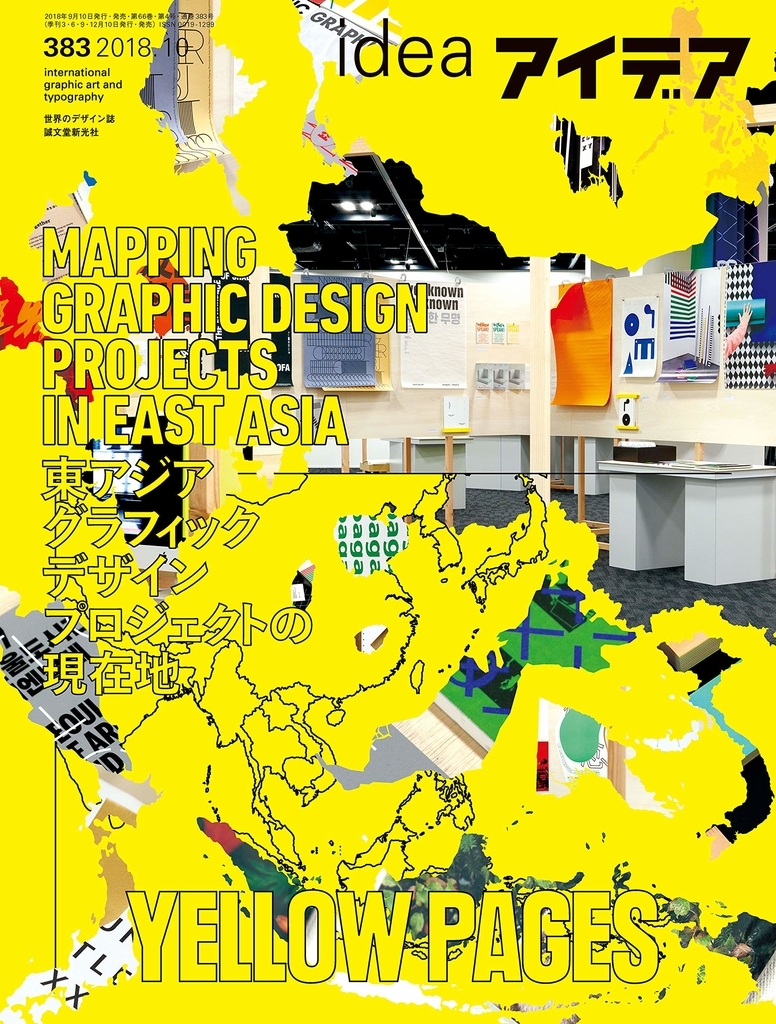
東アジアのグラフィックデザインプロジェクトの現在地を特集した「アイデア 2018年10月号」が誠文堂新光社から2018年9月10日に発売された。
また、デザイン史家・グラフィックデザイナーの佐賀一郎氏による2018年4月27日(金)~7月16日(月・祝)まで横浜開港資料館で開催された「金属活字と明治の横浜――小宮山博史コレクションを中心に」展の展示会レポート記事が掲載。記事では「金属活字と明治の横浜――小宮山博史コレクションを中心に」と小宮山博史氏のコレクションが持つ意義について考察された。
そのほか、長田年伸氏の記事として、2018年6月8日に発売された向井裕一氏著書「日本語組版入門: その構造とアルゴリズム」を読み解く為の『日本語組版入門』に入門するための5つの補助線」なども掲載されている。
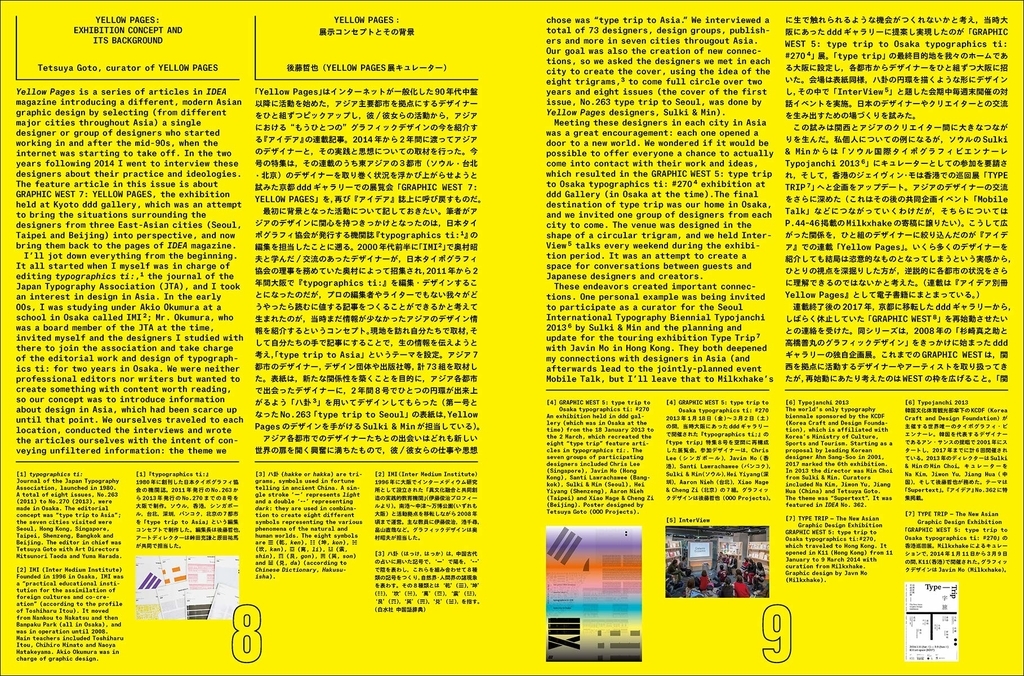
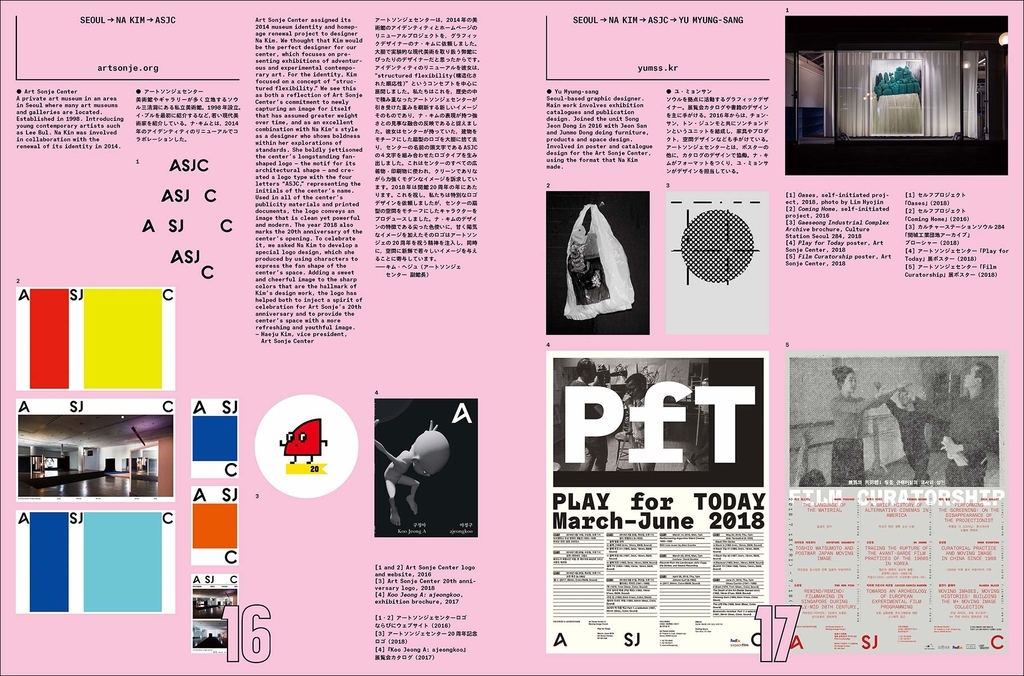
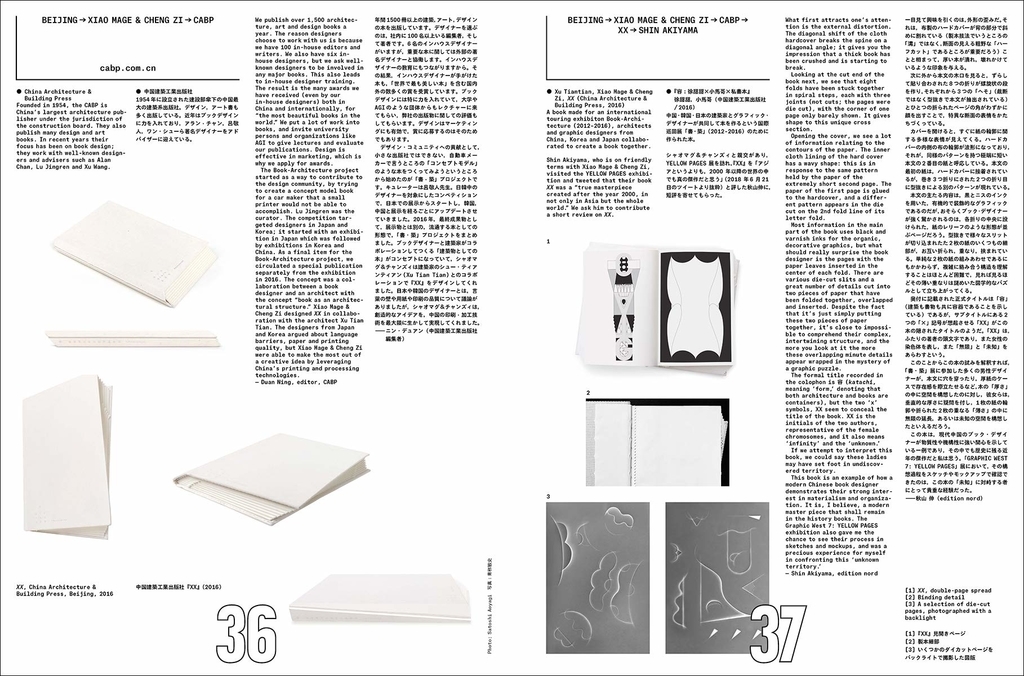
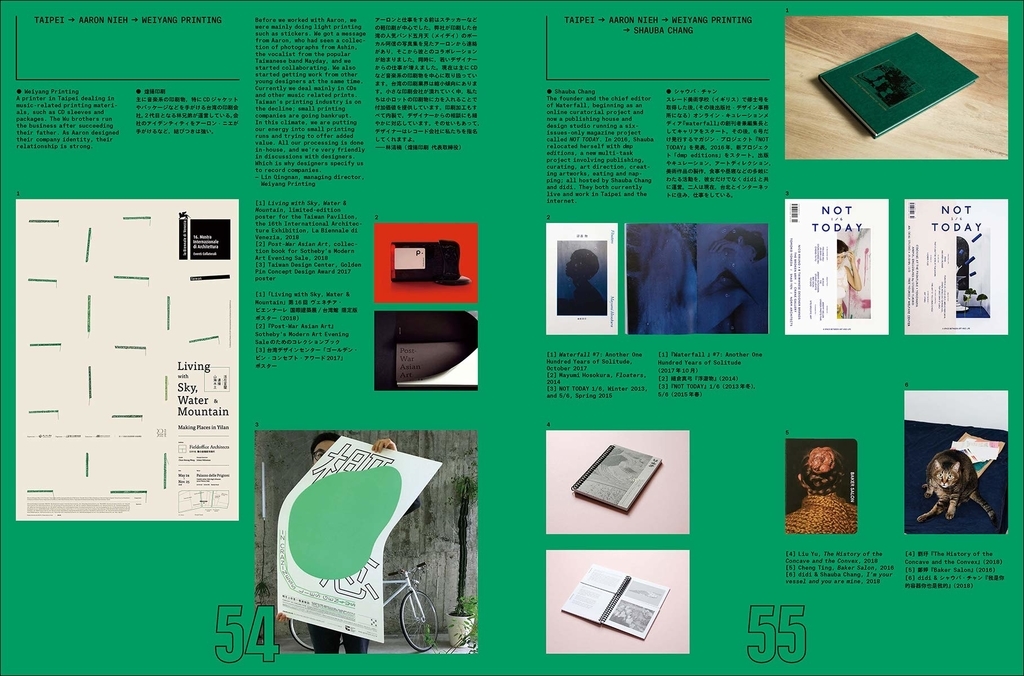
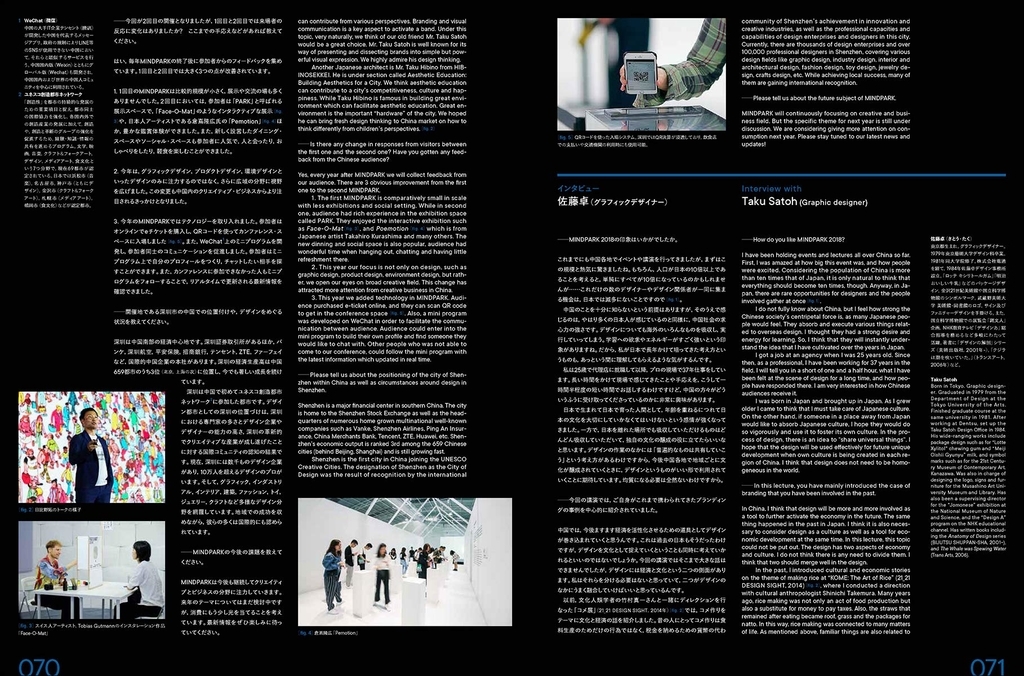
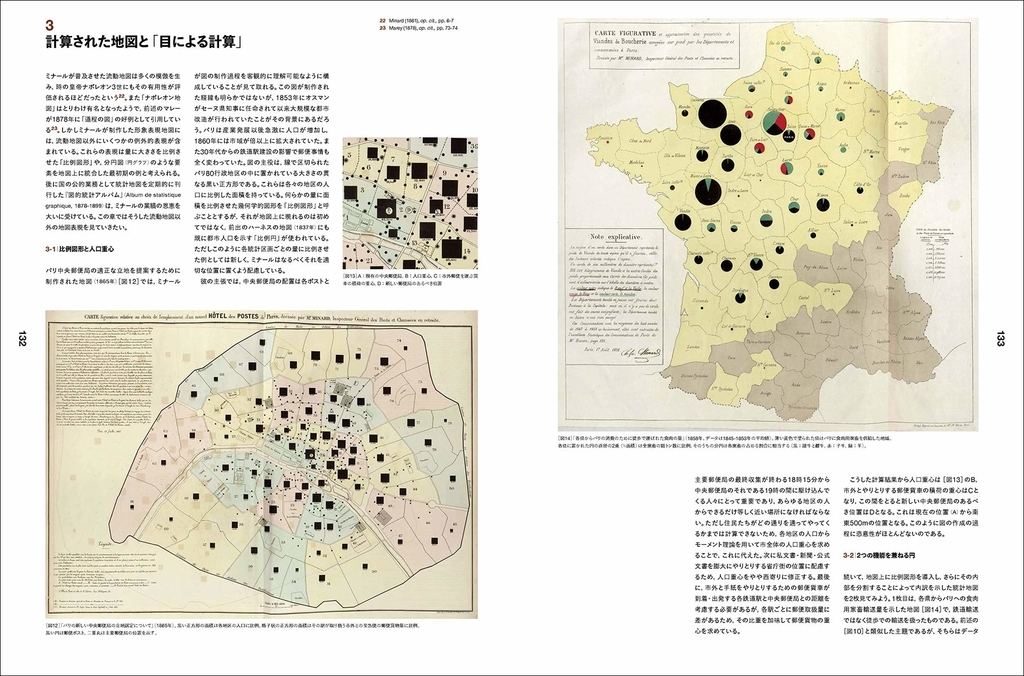
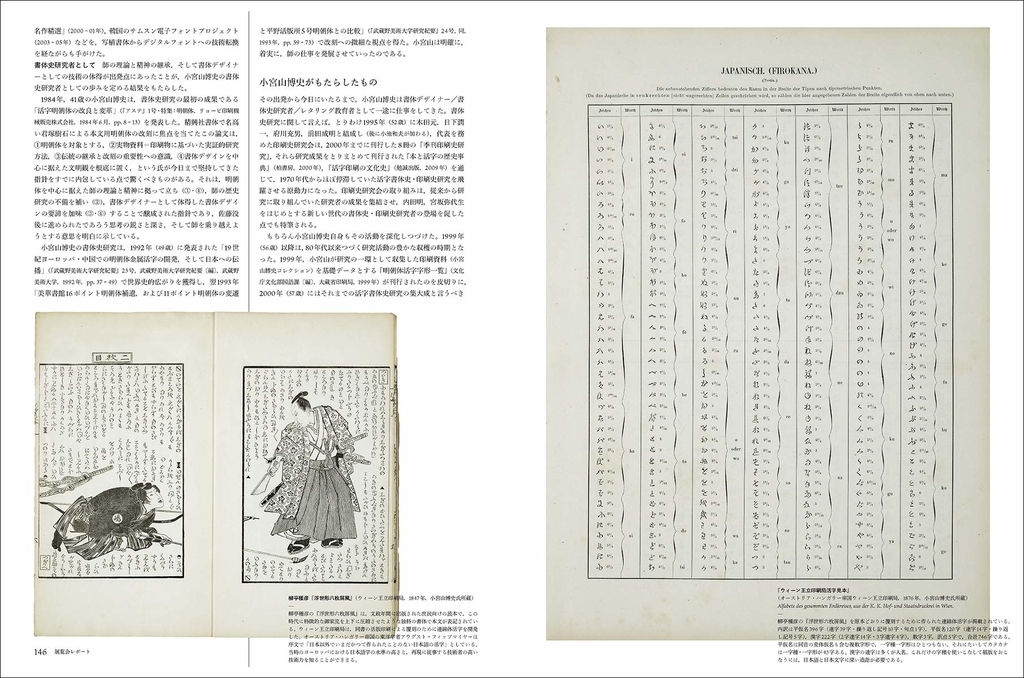
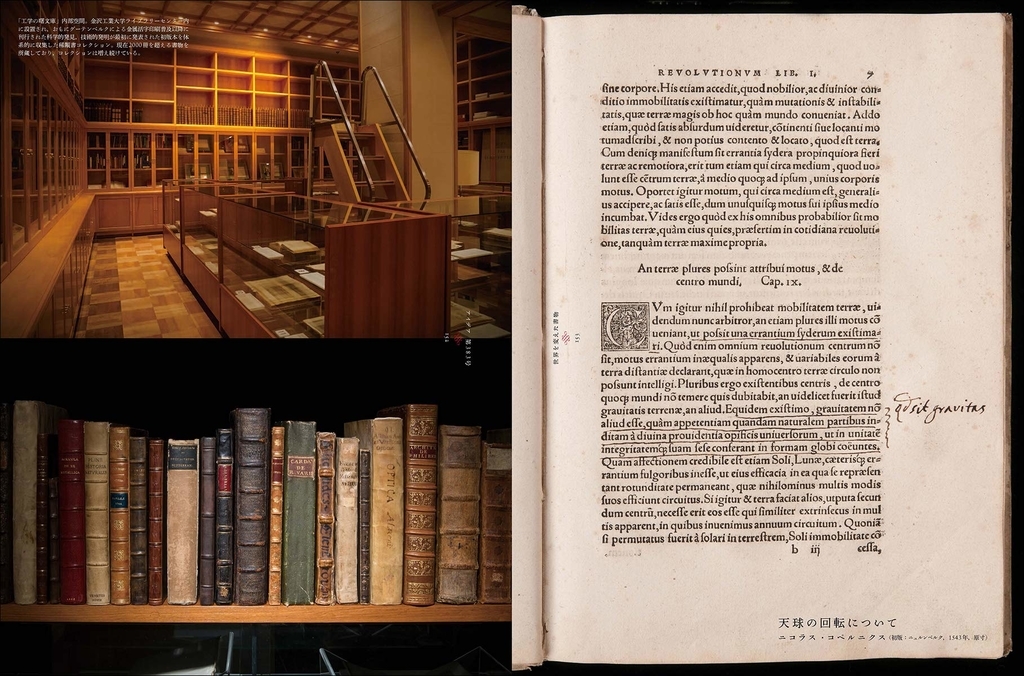
特集:YELLOW PAGES
東アジア グラフィックデザインプロジェクトの現在地
「YELLOW PAGES」は本誌での同名連載を発端とした一連のプロジェクトだ。
連載時には東アジアで活躍する7組のデザイナーへの現地取材を行い、その実践や思想を紹介。
2018年春には京都dddギャラリーで、ソウル・北京・台北の3都市で活躍する3組のデザイナーに焦点をあてた展覧会を行った。
本特集では連載~展示というプロジェクトの経過を誌面に引き戻しつつ、3組の仕事とともに各自のプロジェクトにおける協働関係を紹介。
デザインを規定する社会的・文化的要因を紐解いていくことで、東アジアのグラフィックデザインプロジェクトの現在地を更新する。
YELLOW PAGES:展示コンセプトとその背景
ソウル:ナ・キム
アートソンジェセンター/ユ・ミョンサン/ザ・ブックソサエティ/カン・ムンシク/プロパガンダ/シン・ドクホ/
インデックス/トッププロセス/シンシン
ナ・キムは、韓国発のグラフィックデザイン誌『GRAPHIC』のアートディレクションや展覧会のキュレーションなどの幅広い活動を行うデザイナーだ。
本コーナーでは、アートソンジェセンター(美術館)やプロパガンダ(出版社)などのクライアント、トッププロセス(出版社)などのコラボレーターらとの協働を紹介する。
さらに、それらの協働者が別のデザイナーを紹介することで、ナ・キムというひとりのデザイナーを軸にして、都市への視点が多層化していく試みを行った。
誌面が空間にかわるとき
北京:シャオマグ&チャンズィ
中国建築工業出版社/秋山伸/「書・築」/アートロン
シャオマグ&チャンズィは、本の物質性を際立たせる挑戦的なブックデザインに取り組むデザインデュオ。
本コーナーでは、中国最大手の「建築系出版社」である中国建築工業出版社や、日中韓3ヶ国の建築家とグラフィック・デザイナーが共同して本を作った「書・築」という大型プロジェクトや、
美術印刷を中心に出版やショップ運営などのアートビジネスを展開する「アートロン」、そしてそこから出版されたアートブックの選書などを行った。
主題としてのオブジェクト(もの)――グラフィックデザインを外側から描写する
台北:アーロン・ニエ
ビッグイシュー台湾/華研国際音楽/O.OO/?揚印刷/シャウバ・チャン/經緯印藝/ノス・ブックス
アーロン・ニエは、音楽関連のデザインワークや社会的プロジェクトへ積極的に関与するなど、デザイナーの枠に留まらず広い支持を集めているデザイナーだ。
本コーナーでは、アーロンが表紙のアートディレクションを担当する『ビッグイシュー台湾』、同じく数多くのデザインワークを提供してきたレコード会社の華研国際音楽、
過去にコラボレーションを行ったデザイン事務所のHIM INTERNATIONAL、インディペンデント・パブリッシャーのノス・ブックスなどが紹介される。
CITY TEXT/URE
後藤哲也と萩原俊矢が文字を通して感じる街の肌触りを「CITY TEXT/URE」と名付けて始動したプロジェクト。
ラテン語の「Textus(織る)」を語源に持つTextによって、それぞれの都市にある肌触り(Texture)を切り取るべく、「1 時間以内に」「周りにある」「それぞれの都市を感じさせる」
「Text をモチーフにした」「写真を送る」ことを、複数人のデザイナーに同じタイミングで指示した。本稿は、それぞれが切り取った7日間のTEXT/URE の記録。
BLUE PAGES
連載「YELLOW PAGES」の最終回には、デザインを担当したSulki & Minのチェ・ソンミンと後藤哲也との対談を行うことで連載を振り返った。
本号においても同様に、展覧会終了後に来日したミンと後藤による対談を改めて行い、京都dddギャラリーで行われた展覧会やプロジェクトの今後について話をすすめた。
MINDPARK 2018 REPORT 未来都市とデザイン
中国、深圳を舞台に今年5月に開催されたデザインイベント「MINDPARK 2018」のイベントレポート。
急速な都市化にともない都市デザインへの関心が高まるなかで開催された同イベントについて、主催者や参加デザイナーに話を聞いた。
インタビュー:エリオット・ホアン
インタビュー:佐藤卓
綴じ込み企画:アイデア×ウォレット
『ウォレット』は、ノルウェー・オスロ在住の編集者であるエリス・バイ・オルセンと、デザイナーのモルデザ・ヴァセギを中心に編集・発行されている、ファッション・エディトリアルをテーマにした雑誌。
資本主義的価値の象徴である「ウォレット(財布)」をイメージした判型を採用し、これまでに2号が刊行されている。
このほど同誌の取り扱いが日本の一部書店で始まったことをうけ、過去2号を綴じ込みにし、ダイジェスト版として紹介する。
第28回ブルノ国際グラフィックデザイン・ビエンナーレ 2018
1963年にスタートし、グラフィックデザインの展覧会としてもっとも古い歴史を持つ「ブルノ国際グラフィックデザイン・ビエンナーレ」。
その第28回が2018年5月から8月にかけて開催された。ビエンナーレそのものに自己批判的な態度をとった前回展に対して、新たなキュレーター陣をむかえた今回展ではどのようなアップデートがなされたのだろうか。
本稿では、キュレーターを務めたデザインチームOKOLOの協力のもと、国際展の内容を中心にその様子をレポートする。
寄稿:ビエンナーレを振り返って
文:OKOLO
連載│アトラス考─生態学的世界観の視覚化
第6回 シャルル・ジョゼフ・ミナールの流動地図――運河・鉄道時代の空間組織
連載6回目のテーマは「流動地図」。19世紀始めに鉄道が登場することによって、近代国家は国土空間を一大産業体として再組織化していくこととなる。
そして、こうした時代を生きたフランスの土木技師、シャルル・ジョゼフ・ミナールの統計地図は、インフラストラクチャーの革新がもたらす社会経済の構造的変化を映し出した鏡でもあった。
その地図の最大の特徴は、視覚によって迅速に量的関係が把握できるということにあり、そこには「ものを言う地図」の思想があった。
小宮山博史と明朝体
展覧会レポート 金属活字と明治の横浜――小宮山博史コレクションを中心に
文・解説:佐賀一郎
デザイン:長田年伸
横浜開港資料館で「金属活字と明治の横浜――小宮山博史コレクションを中心に」展が開催された。
展覧会タイトルが示すように、書体史研究家・小宮山博史のコレクションを中心に構成された同展は、明朝体の歴史的変遷を、日本のみならず世界的な規模でたどることのできる内容である。
本記事では、デザイン史家・グラフィックデザイナーの佐賀一郎が、同展および小宮山コレクションがもつ意義について考察した。
世界を変えた書物 金沢工業大学「工学の曙文庫」
デザイン:長田年伸
金沢工業大学にある「工学の曙文庫」は、エポックメイキングとなった科学的発見や技術的発明の原典を収集したライブラリーである。
2018年9月8日から上野の森美術館では「世界を変えた書物」展が開催され、貴重なコレクションに触れる機会を提供している。
本記事では、文筆家・山本貴光が同文庫の所蔵する書物への考察を行い、「知を連環させる」装置としてのブックデザイン論を展開する。
知の連環、思考の装置としての本 マルジナリアを読み解く
文:山本貴光
『日本語組版入門』に入門するための5つの補助線
文・デザイン:長田年伸
2018年6月に刊行された向井裕一著『日本語組版入門』(誠文堂新光社)の入門記事。
同書では、日本語組版を覚えるための「ルール」から組み立てるための「考え方」へ、その構造と設計のための考え方が図式化して分かりやすく解説されている。
「全角ベタ組み」を基本とする日本の組版形成術が、そこに存在するプロトコル(手続き)を詳らかにしていくことによって明らかになっていく。
takeo paper show 2018「precision」レポート
路上にて
文:永原康史
写真:山中慎太郎(Qsyum!)
今年で48回目を数える「takeo paper show」のレポート。
「precision(精度)」がテーマとなった今回展では、紙に内在する精密さを呼び覚ますことで、プロダクトや建築、医療などさまざまな分野に対応しうる紙の潜在力が追求されることとなった。
さらに、出品者は展示物の制作だけでなく、それを実現するための「新しい紙」の考案も行ったという点で本展はユニークであり、本記事ではその詳細も紹介していく。
「trip to zine ~zineへの旅~」展 レポート
文:高橋創一
デザイン:佐藤豊
宮城県にある多賀城市立図書館3階ギャラリーで「trop to zine ~zineへの旅~」展が開催された。
仙台を中心に活動するBook!Book!Sendaiの企画による同展は、2017年に刊行された『日本のZINEについて知ってることすべて』をきっかけに構想されることとなった。
日本語組版を設計するためには、ルールや方針の背景にある構造と原理を理解することが必要です。
本書では組版を「覚えるべき慣習的なルール」ではなく、組版を形成する要素とその属性の組み合わせによるプログラムとして整理。
日本語の記述システムや組版の技術的構造を踏まえたうえで、印刷からオンスクリーンまであらゆる場面に対応する考え方を解説します。
本書ではさらに、組版とページ版面、使用する書体のデザインそれぞれの関係性についても分析・考察。
日本語情報処理を越えたトータルな日本語タイポグラフィへの視点も提示します。
巻末には現場的なニーズにもすぐに対応できるAdobe InDesign CCの設定例一覧も収録。
従来のルールブックの枠組をアップデートし、これからのスタンダードとなる一冊です。
向井裕一Profile●1957年大阪生まれ。デザイナー。グラフィックデザイン、デジタル・パブリケーションに関連する企画・編集・デザインを手がける。著書に『日本語組版の考え方』(誠文堂新光社)、共著に『香港―多層都市』(東方書店)、編著に『基本 日本語活字集成OpenType版』(誠文堂新光社)。